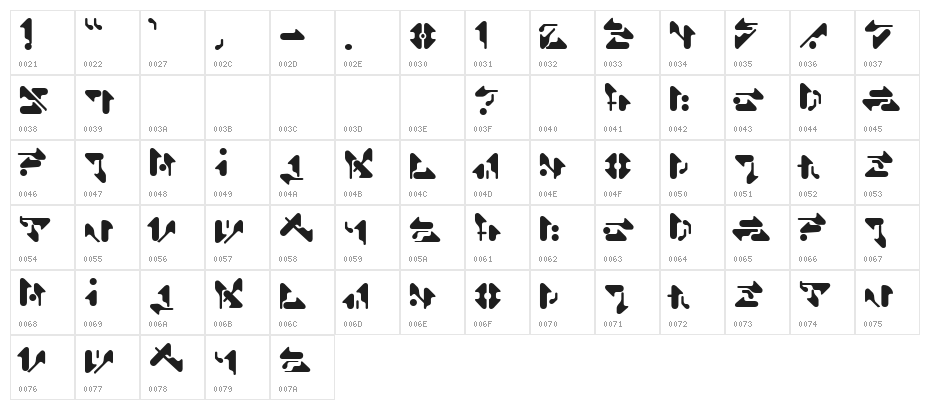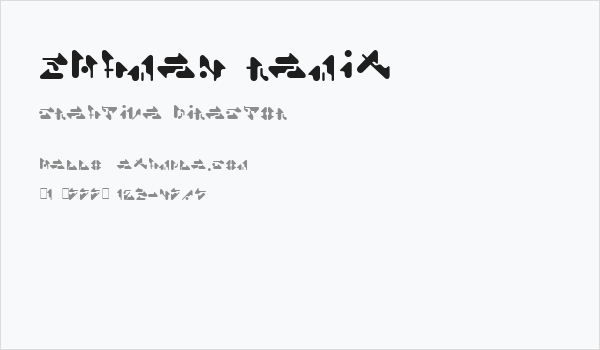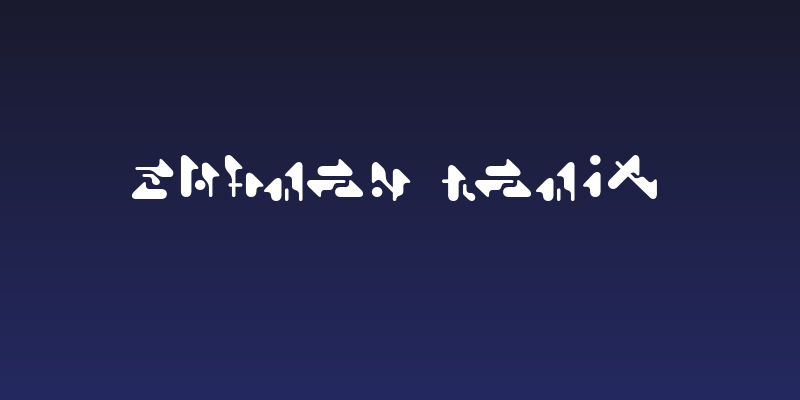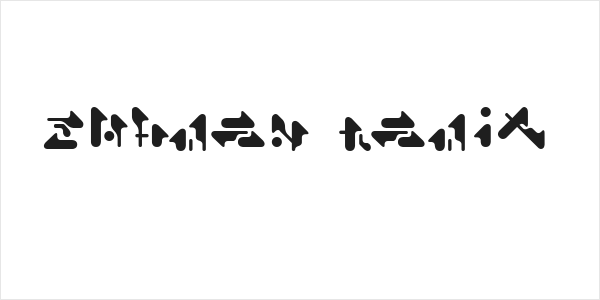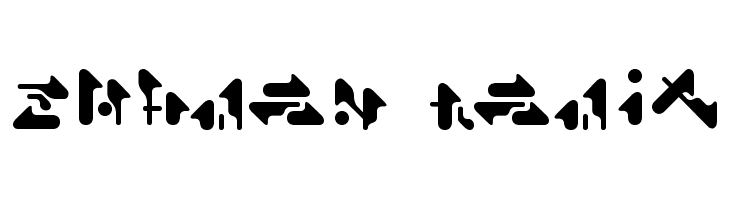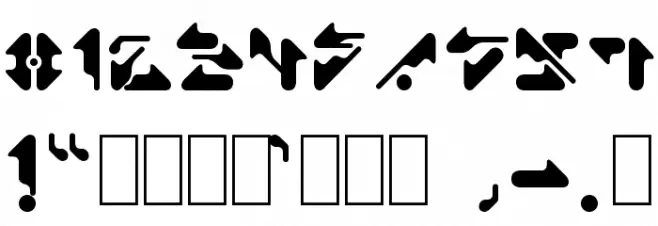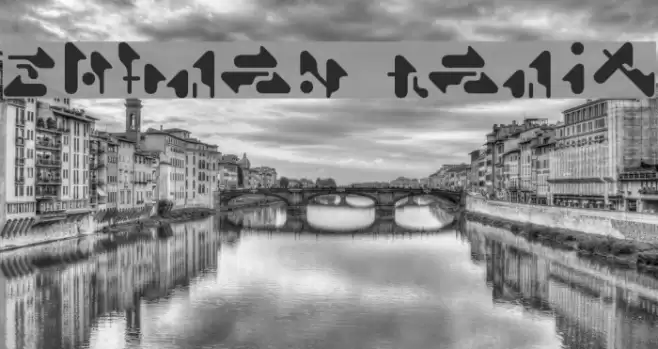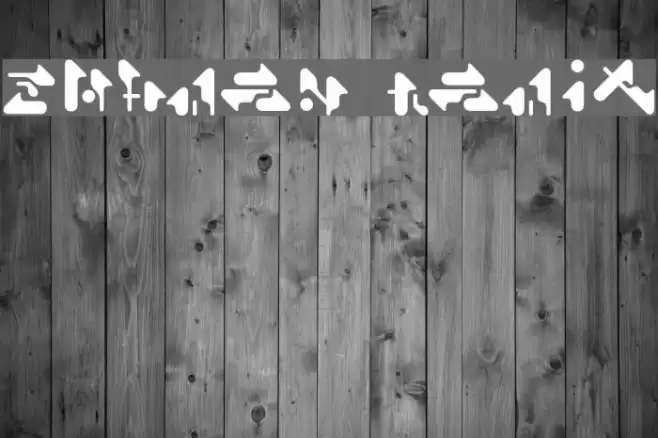
Shamen Remix Font
| Stil general | Futuristic, Abstract |
| Caz de utilizare | Logos, Posters, Titles |
| Proiecte propuse | Ideal for sci-fi themed designs, video game graphics, movie posters, or any project needing a mysterious, futuristic look. |